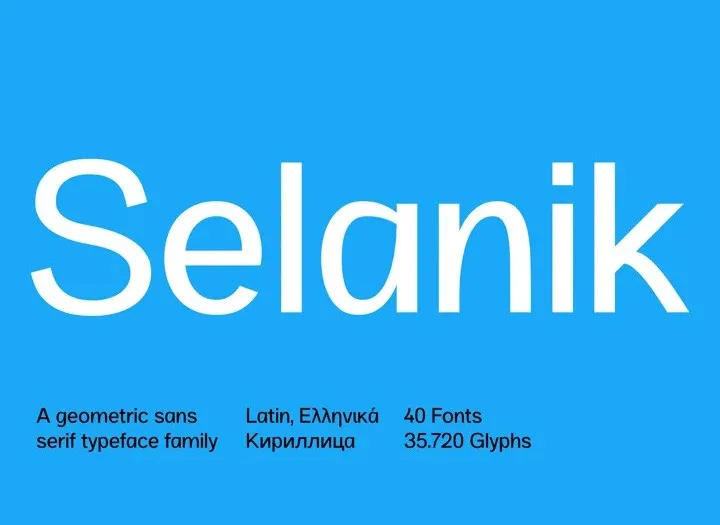
A SK Selanik Font é uma seleção única de tipo gótico, desenvolvida pelo site de concursos de design 99designs. Este estilo moderno e minimalista traz uma naturalidade ao seu projeto, dando-lhe um ar elegante e atraente. Nomes como Thessaloniki podem ter muitos significados históricos, mas a SK Selanik font não se preocupa com isso de maneira alguma. Em vez disso, ela captura o espírito contemporâneo da cidade grega. Esta tipografia é uma fusão perfeita entre o passado e o futuro do design. Ela representa as texturas históricas de Thessaloniki através de formas modernas. Com SK Selanik Font, você não apenas adicionará um toque moderno a seu projeto gráfico, como também terá à disposição uma fonte com movimento natural que dará vida aos seus elementos design. Este tipo é ideal para uso em aplicações digitais e impressivas, tornando o seu trabalho ainda mais atraente e sofisticado.